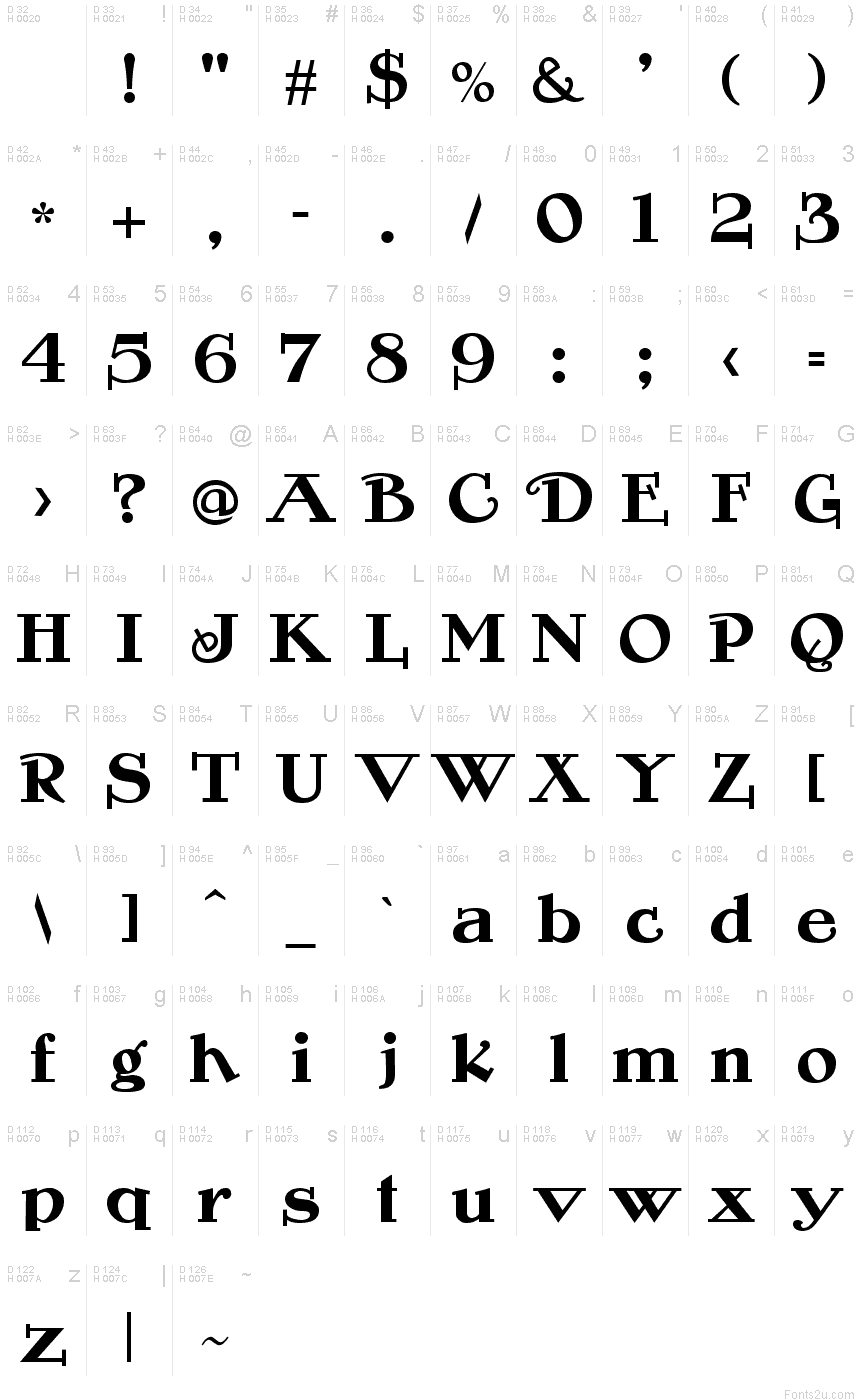
Rogers
Rogers, bezpłatny krój szeryfowy w dawnym stylu autorstwa Erica Grunina, ma literacki, lekko historyczny klimat, który zawdzięcza szerokim łukom, miękkim, klinowatym wykończeniom i kaligraficznemu stylowi wersalików. Litery sprawiają wrażenie osadzonych i intelektualnych, a nie sztywnych; dzięki hojnej krągłości i kilku ostro zakończonym detalom, alfabet nie jest nudny ani zbyt ułożony.
Doskonale odnajduje się w projektach wydawniczych i kulturalnych: okładki książek, nagłówki magazynów, plakaty teatralne, plansze tytułowe i monogramy to świetne zastosowania dla tego darmowego fontu. Użyj go, gdy zależy Ci na klasycznym brzmieniu z odrobiną polotu, zwłaszcza w krótkich nagłówkach i na okładkach, gdzie te zaokrąglone formy i żywe wielkie litery samodzielnie nadają charakter całości.